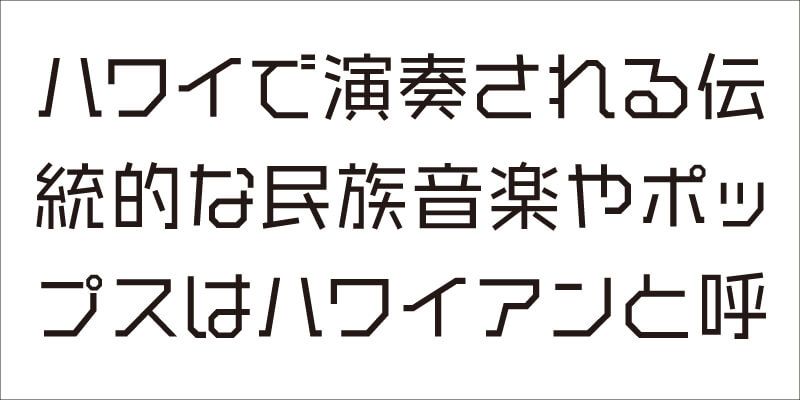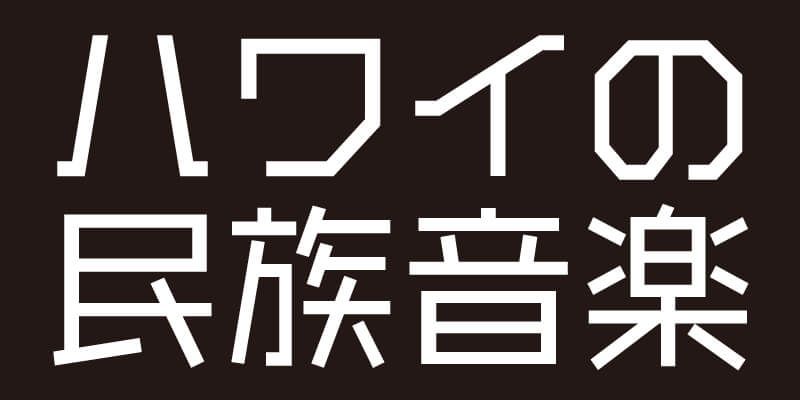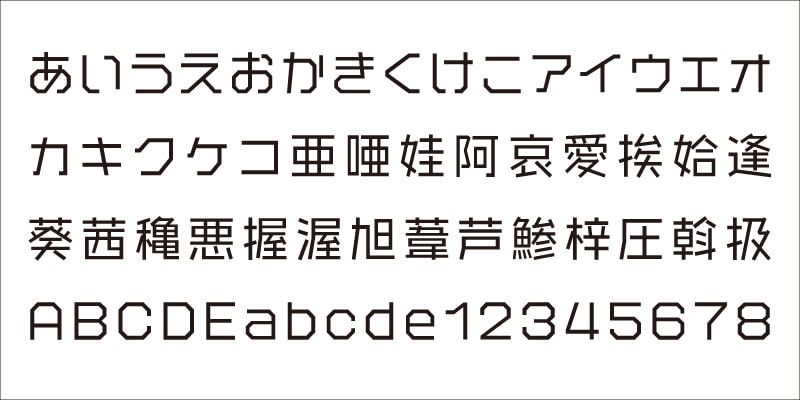
Todos los caracteres de este tipo de letra gótica (sans-serif) comparten trazos con claras líneas rectas, pero las formas de las letras conservan una suavidad y elegancia. En contraste con sus ideogramas compuestos por líneas simples y rectas, como si estuvieran diseñados con fragmentos de cinta de papel, el diseño de los caracteres silábicos kana se basa en un octógono. Con este tipo de letra, el texto compuesto tendrá fuerza visual y alegría.